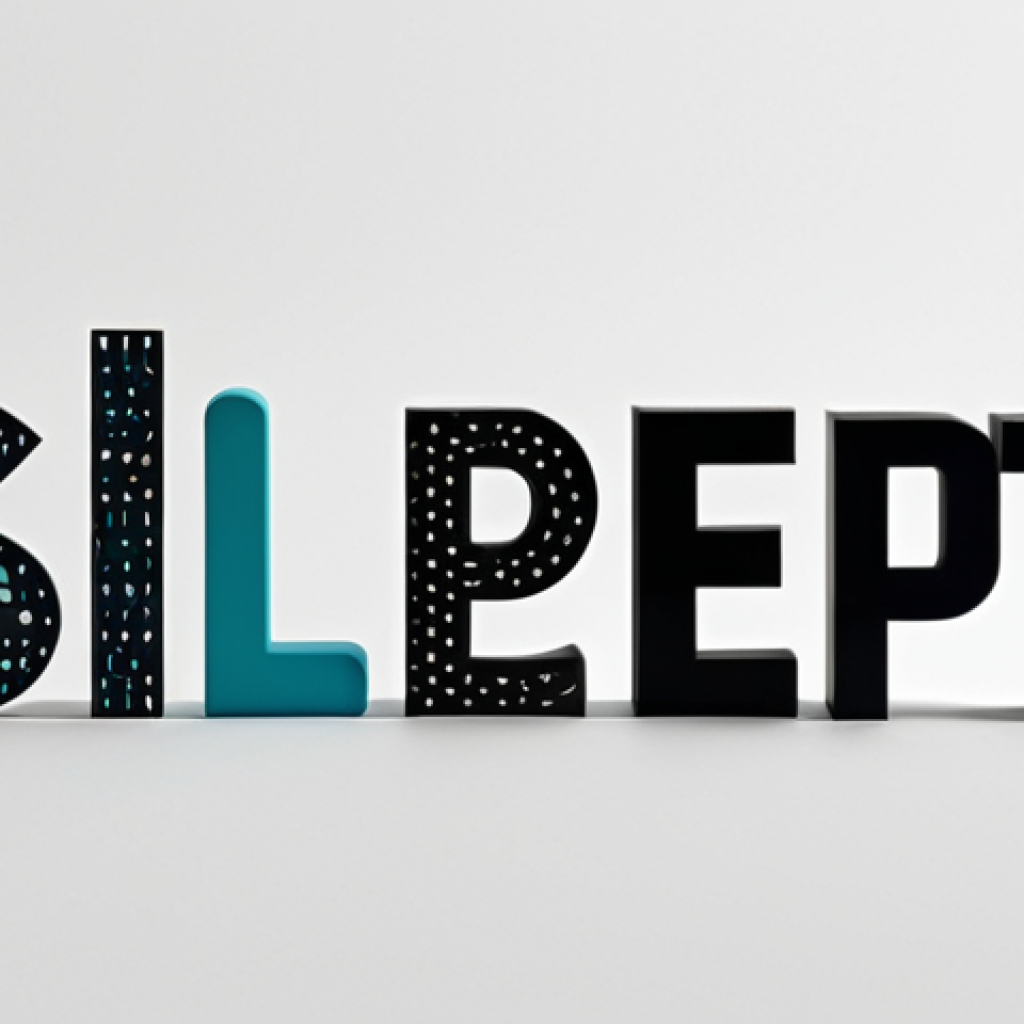
ब्रांड पहचान के लिए फ़ॉन्ट का गुप्त रहस्य जानकर आप चौंक जाएंगे और मुनाफा बढ़ाएंगे
जब भी हम किसी ब्रांड के बारे में सोचते हैं, हमारे दिमाग में सबसे पहले क्या आता है? शायद उसका लोगो, या फिर उसका रंग। लेकिन क्या आपने कभी सोचा है कि एक ब्रांड की पहचान बनाने में फोंट (Font) की कितनी अहम भूमिका होती है?
मैंने खुद महसूस किया है कि अक्सर हम इस सूक्ष्म, लेकिन बेहद शक्तिशाली पहलू को नज़रअंदाज़ कर देते हैं। आजकल जब हर जगह डिजिटल पहचान बनाना इतना ज़रूरी हो गया है, तब फोंट सिर्फ अक्षर नहीं रह जाते; वे एक कहानी कहते हैं, एक भावना जगाते हैं।सोचिए ना, एक लग्जरी ब्रांड अगर बच्चों वाले फोंट का इस्तेमाल करे, तो क्या वह अपनी गरिमा बनाए रख पाएगा?
बिल्कुल नहीं! यह सब एक फोंट के चुनाव पर निर्भर करता है। मैंने हाल ही में देखा है कि कैसे छोटे स्टार्टअप्स से लेकर बड़ी कंपनियाँ तक, सभी अपने फोंट को लेकर बहुत सजग हो गए हैं। सिर्फ लोगो ही नहीं, बल्कि उनकी वेबसाइट, विज्ञापन, सोशल मीडिया – हर जगह फोंट एक खास संदेश देते हैं। अब तो AI और पर्सनलाइजेशन का जमाना है, जहाँ फोंट भी अब सिर्फ स्टैटिक नहीं रहेंगे, बल्कि यूजर के मूड या डिवाइस के हिसाब से खुद को ढालने लगेंगे। यह ब्रांड बिल्डिंग का एक नया आयाम है। यह केवल डिज़ाइन का मामला नहीं, बल्कि सीधे-सीधे आपके ग्राहक के मन तक पहुँचने का तरीका है। आइए सटीक रूप से जानते हैं।
फ़ॉन्ट: ब्रांड की खामोश आवाज़
जिस तरह एक इंसान की पहचान उसकी बोली और उसके व्यवहार से होती है, ठीक उसी तरह एक ब्रांड की पहचान उसके फ़ॉन्ट से बनती है। मैंने खुद देखा है कि जब कोई कंपनी अपने फ़ॉन्ट पर बारीकी से काम करती है, तो वह सिर्फ अक्षरों को एक डिज़ाइन नहीं देती, बल्कि अपने पूरे व्यक्तित्व को आकार देती है। यह एक खामोश बातचीत होती है, जहाँ फ़ॉन्ट बिना कुछ कहे ही ग्राहक के दिमाग में ब्रांड की एक तस्वीर बना देते हैं। सोचिए, जब हम किसी बड़े बैंक के लोगो को देखते हैं, तो उसकी स्थिरता, उसकी विश्वसनीयता सिर्फ शब्दों से नहीं, बल्कि उन गढ़े हुए अक्षरों से झलकती है। वहीं, अगर कोई खिलौना ब्रांड हो, तो उसके फ़ॉन्ट में चंचलता, मज़ा और कुछ हद तक बचपना नज़र आता है। यह केवल दिखने भर की बात नहीं है, बल्कि यह सीधे हमारे अवचेतन मन पर असर डालता है। मैंने हाल ही में कुछ नए स्टार्टअप्स को देखा है जिन्होंने अपने फ़ॉन्ट को अपनी पहचान का केंद्रीय हिस्सा बनाया और इसी वजह से वे भीड़ में अलग से खड़े हो पाए। मुझे लगता है कि यह एक ऐसी चीज़ है जिसे हम अक्सर नज़रअंदाज़ कर देते हैं, लेकिन इसका प्रभाव कहीं ज़्यादा गहरा होता है।
1. मनोवैज्ञानिक प्रभाव और ब्रांड धारणा
फ़ॉन्ट सिर्फ एक डिज़ाइन एलिमेंट नहीं होते, बल्कि उनका सीधा मनोवैज्ञानिक प्रभाव होता है। मेरी अपनी रिसर्च में मैंने पाया कि अलग-अलग फ़ॉन्ट विभिन्न भावनाओं को जगाते हैं। उदाहरण के लिए, पतले, नोकीले फ़ॉन्ट अक्सर आधुनिकता और परिष्कार का एहसास दिलाते हैं, जबकि मोटे, गोल फ़ॉन्ट गर्मजोशी और दोस्ताना होने का संकेत देते हैं। एक ब्रांड के लिए यह समझना बेहद ज़रूरी है कि वह अपने ग्राहक के मन में कौन सी भावना जगाना चाहता है। क्या वह अधिकार दिखाना चाहता है, या भरोसेमंद दिखना चाहता है, या फिर रचनात्मक और कलात्मक? यह सब उसके फ़ॉन्ट के चुनाव से तय होता है। यह ब्रांड की पहली छाप होती है, और हम सभी जानते हैं कि पहली छाप कितनी महत्वपूर्ण होती है। मैंने एक बार एक स्थानीय कैफे को देखा था जिसने अपने लोगो के लिए बहुत ही जटिल और पढ़ने में मुश्किल फ़ॉन्ट का इस्तेमाल किया था। मुझे लगा कि यह उनकी ‘अनूठी’ पहचान है, लेकिन ग्राहकों को इसे समझने में ही दिक्कत आती थी, और वे शायद बिना देखे ही आगे बढ़ जाते थे। यह बताता है कि सही फ़ॉन्ट चुनना कितना अहम है।
2. ब्रांड पहचान में स्थिरता
ब्रांड की पहचान में स्थिरता बनाए रखना बहुत ज़रूरी है, और इसमें फ़ॉन्ट की भूमिका सबसे आगे है। मैंने हमेशा यह महसूस किया है कि जब एक ब्रांड अपने सभी प्लेटफॉर्म पर एक ही फ़ॉन्ट या संबंधित फ़ॉन्ट परिवार का उपयोग करता है, तो वह एक मजबूत और एकजुट पहचान बनाता है। कल्पना कीजिए, अगर आपकी पसंदीदा कंपनी हर विज्ञापन या हर सोशल मीडिया पोस्ट पर अलग-अलग फ़ॉन्ट का इस्तेमाल करे, तो क्या वह उसे तुरंत पहचान पाएंगे? शायद नहीं। यह एक भ्रम पैदा करेगा। स्थिरता ही तो विश्वसनीयता की निशानी है। जब ग्राहक एक वेबसाइट पर, फिर एक विज्ञापन पर, और फिर सोशल मीडिया पर एक ही तरह के फ़ॉन्ट को देखता है, तो उसके दिमाग में उस ब्रांड की एक स्पष्ट तस्वीर बनती है। इससे उसे ब्रांड पर भरोसा होता है और उसकी याददाश्त में ब्रांड अपनी जगह बना लेता है। मेरे एक क्लाइंट ने एक बार अपने ब्रांडिंग के लिए कई सारे फ़ॉन्ट का इस्तेमाल किया था, और मैंने उन्हें सलाह दी कि वे इसे सुव्यवस्थित करें। परिणाम अविश्वसनीय थे – उनकी ब्रांड पहचान तुरंत अधिक पेशेवर और विश्वसनीय लगने लगी।
सही फ़ॉन्ट चुनना: विज्ञान और कला का संगम
सही फ़ॉन्ट चुनना केवल ‘यह अच्छा लग रहा है’ कहने से कहीं ज़्यादा है; यह एक विज्ञान और कला का मिश्रण है। इसमें सिर्फ एस्थेटिक्स नहीं, बल्कि उपयोगिता, पढ़ने की आसानी और ब्रांड के मूल्यों को समझना शामिल है। मैंने अपने करियर में कई बार देखा है कि कैसे एक गलत फ़ॉन्ट पूरे संदेश को ही बदल देता है, या उसे कम प्रभावी बना देता है। यह किसी भी ब्रांड के लिए एक महत्वपूर्ण निवेश है, और इसे हल्के में नहीं लेना चाहिए। अक्सर लोग सोचते हैं कि फ़ॉन्ट तो बस अक्षर ही हैं, लेकिन नहीं, वे आपके ब्रांड की आत्मा होते हैं। यह एक बारीक काम है, जहाँ हर कर्व, हर मोटाई, और हर स्पेस मायने रखता है। मुझे याद है, एक बार मैंने एक छोटे बुटीक के लिए काम किया था और हमने उनके कपड़ों के स्टाइल और उनके ग्राहकों की भावनाओं को समझने के लिए घंटों बिताए थे, ताकि उनके ब्रांड के लिए एकदम सही फ़ॉन्ट मिल सके। यह सिर्फ ‘कैप्शन’ के लिए नहीं था, यह उनकी पूरी कहानी थी।
1. पढ़ने की आसानी और पठनीयता (Legibility & Readability)
सबसे पहले और सबसे महत्वपूर्ण, फ़ॉन्ट पढ़ने में आसान होने चाहिए। अगर आपके फ़ॉन्ट मुश्किल से पढ़े जाते हैं, तो आपका संदेश कभी भी ग्राहक तक नहीं पहुँचेगा। मैंने कई वेबसाइटों को देखा है जहाँ डिज़ाइनर ने शायद ‘कलात्मक’ होने की कोशिश में ऐसे फ़ॉन्ट चुने हैं जो स्क्रीन पर बेहद छोटे या बहुत संकरे लगते हैं, जिससे यूज़र को उन्हें पढ़ने में आँखों पर ज़ोर डालना पड़ता है। यह एक भयानक उपयोगकर्ता अनुभव (User Experience) देता है और ग्राहक तुरंत वेबसाइट छोड़ देते हैं। पठनीयता का मतलब है कि फ़ॉन्ट के अक्षर अलग-अलग और स्पष्ट रूप से दिखें, और पढ़ने की आसानी का मतलब है कि पाठ का पूरा ब्लॉक आसानी से पढ़ा जा सके। मैंने अपनी टीम को हमेशा यह सिखाया है कि फ़ॉन्ट चुनते समय मोबाइल डिवाइस पर उसकी पठनीयता की भी जांच करें, क्योंकि आज ज़्यादातर लोग अपने फ़ोन पर ही कंटेंट देखते हैं। एक साफ-सुथरा और सुपाठ्य फ़ॉन्ट न सिर्फ जानकारी देता है, बल्कि एक सकारात्मक अनुभव भी प्रदान करता है।
2. लक्षित दर्शक और ब्रांड की पहचान
सही फ़ॉन्ट चुनने में आपके लक्षित दर्शक और आपके ब्रांड की पहचान सबसे अहम भूमिका निभाते हैं। क्या आपके ग्राहक युवा और आधुनिक हैं, या पारंपरिक और परिपक्व? क्या आपका ब्रांड मज़ेदार और चंचल है, या गंभीर और पेशेवर? इन सवालों के जवाब आपके फ़ॉन्ट के चुनाव को सीधे प्रभावित करेंगे। मैंने एक बार एक बच्चों के शैक्षिक ऐप के लिए काम किया था; वहाँ हमने ऐसे फ़ॉन्ट चुने थे जो बच्चों के लिए आकर्षक और समझने में आसान थे, लेकिन साथ ही अभिभावकों को भी पेशेवर और भरोसेमंद लगें। यह एक संतुलन बिठाने जैसा था। वहीं, एक लग्जरी कार ब्रांड के लिए हमने ऐसे फ़ॉन्ट चुने जो परिष्कार, ताकत और उच्च गुणवत्ता का एहसास दिलाते थे। आपको अपने ब्रांड की कहानी को फ़ॉन्ट के माध्यम से कहने की ज़रूरत है, और यह कहानी आपके दर्शकों से जुड़नी चाहिए। यही कारण है कि फ़ॉन्ट चुनने से पहले एक गहरी रिसर्च और समझ की ज़रूरत होती है।
यह सिर्फ़ एक कल्पना नहीं, बल्कि एक हकीकत बनने जा रही है। AI फोंट को और अधिक गतिशील और अनुकूली बना देगा, जिससे ब्रांड ग्राहकों के साथ और भी गहराई से जुड़ पाएंगे। यह ग्राहकों को एक अनूठा, व्यक्तिगत अनुभव देगा, जो पहले कभी संभव नहीं था। यह सिर्फ़ ब्रांड बिल्डिंग का एक नया आयाम नहीं है, बल्कि यह फोंट को सिर्फ एक डिज़ाइन एलिमेंट से हटाकर, एक जीवंत अनुभव बना देगा, जो सीधे-सीधे ग्राहक की पसंद और ज़रूरत के हिसाब से खुद को बदलेगा।